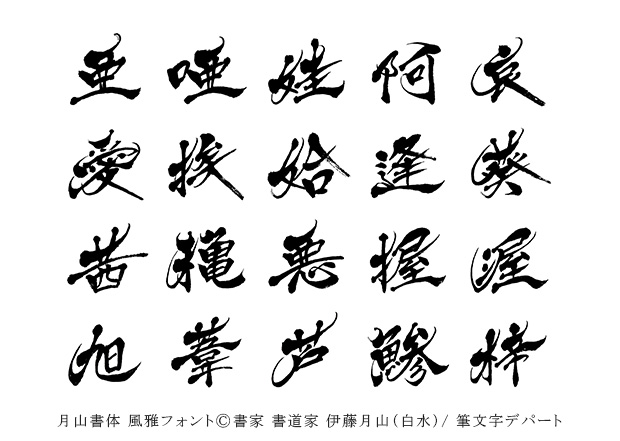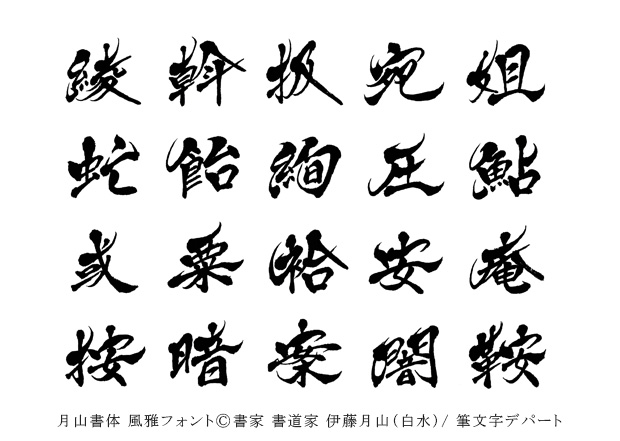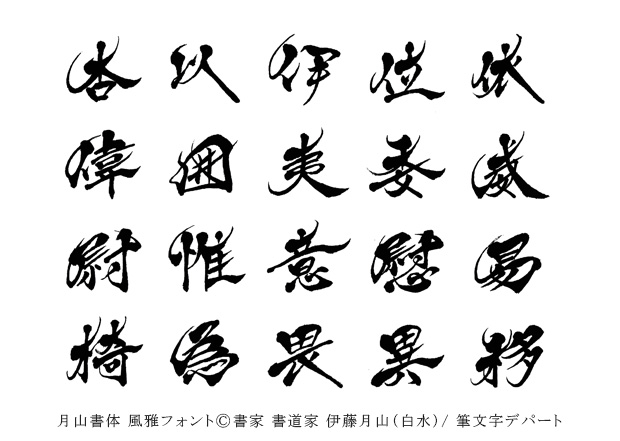
上品さと高級感が漂う「風雅」フォント
この『風雅』フォントは、書家/書道家 伊藤月山の素養を活かして創り出したもので上品さ、高級感、洗練された美しさが調和した現代的なデザインです。また、月山の得意とする『風の動きの表現』を独自の感性で仕上げており、1文字でもロゴになり得る唯一無二の筆文字フォントです。
【風雅フォントの見本】
雅やかな雰囲気と高級感、そして洗練された美しさが特徴の手書き書体「風雅フォント」の見本(サンプル)一覧です。 和文フォント「月山書体 風雅」は書道家の伊藤月山が考案した大人の雰囲気が漂う筆文字デザインです。 毛筆書体のやや細字フォント文字「風雅」が新発売。パッケージ、看板、動画などに商用利用が可能です。
墨の滲みを表現
アンカーポイント多く墨の滲みを具象化したフォントです。書道の息吹を感じることができます。
個性的なデザイン
風の舞フォントの書体は書家/書道家 伊藤月山(白水)が独自に考案した構成法「風舞書®」を応用した、完全オリジナルの個性的な毛筆書体です。また漢字の偏(へん)や旁(つくり)の使い回しは一切せず1文字ずつ手書きで丁寧に書き上げました。